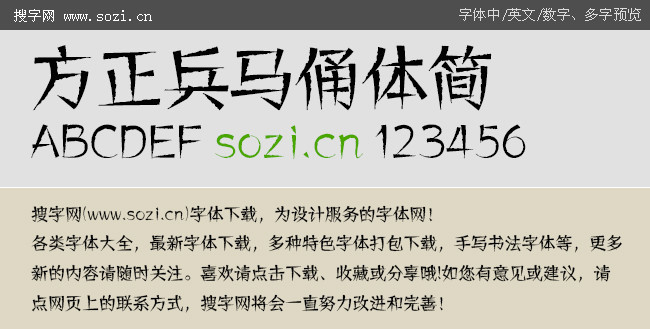
方正兵馬俑體簡
搜字網(wǎng)提供一款方正兵馬俑體簡中文字體下載,方正兵馬俑體傳達(dá)出不同的價(jià)值觀訴求,不同的審美取向,不同的人文特征。 是一款描述歷史、詮釋滄桑、抱樸守靜、彰顯耐力的排版文字。 同時(shí)也是古今語境的接引者。能夠適用于藝術(shù)設(shè)計(jì)、包裝印刷、圖形設(shè)計(jì)等應(yīng)用。